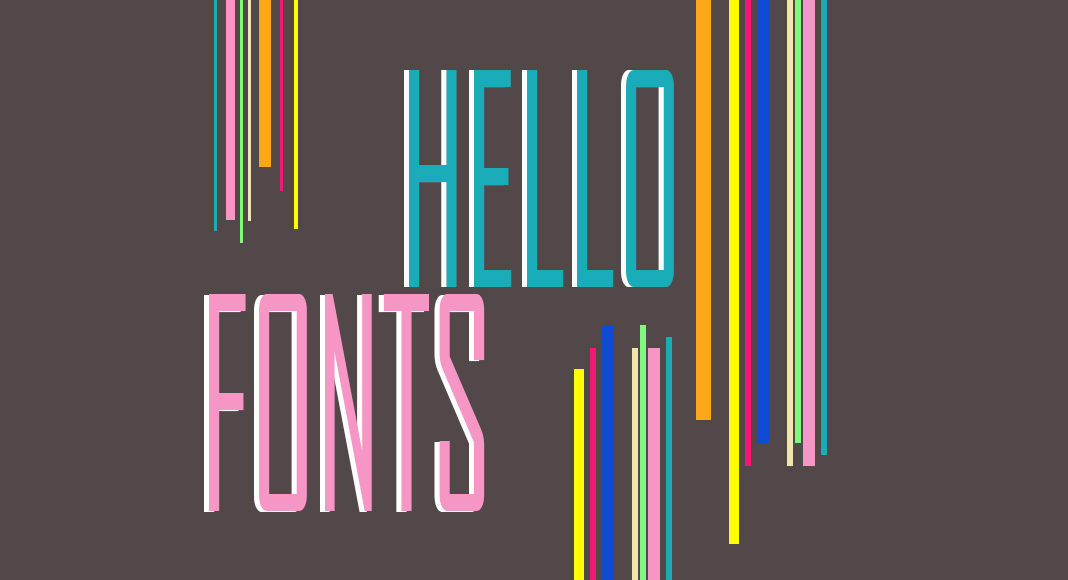
Manchmal geht es nur um wenige Millimeter. Statt beim herkömmlichen Font zu spationieren, bietet es sich an, von Anfang an eine schmale Schriftart zu wählen. Doch auch aus stilistischen Gründen kann sich ein engeres Schriftbild gutmachen. In unserer Sammlung unten findet sich für jeden Geschmack und Anlass etwas.
Schmale SchriftartSaira Condensed
Saira Condensed bietet insgesamt neun Schriftschnitte. Wünschen Sie die Schrift noch etwas komprimierter, finden Sie in den Google Fonts zudem Saira Extra Condensed.
Stint Ultra Condensed
Trotz seines extrem schmalen Schriftbilds ist Stint Ultra Condensed gut lesbar.
• Design: Astigmatic One Eye Typographic Institute
Schmale SchriftartCabin Condensed
Diese schmale Schriftart ist eine komprimierte Variante der Cabin-Schriftfamilie, für die sich die Designer von Schriften von Eric Gill und Edward Johnston inspirieren ließen.
• Design: Impallari Type
Schmale SchriftartBarlow Condensed
Barlow Condensed ist ein Kind Kaliforniens. Zumindest ist es der Schrift auf Straßenschildern und Autokennzeichen des Golden State nachempfunden.
Blue Highway
Highway meint in diesem Fall tatsächlich die Autobahn, und zwar die im Norden der USA und in Kanada. Von den Schildern auf diesen Schnellstraßen stammt die Vorlage für diesen Font.
Schmale SchriftartCopper Canyon
Der Font basiert auf Adobe Poplar, ist aber deutlich massiver.
Wire One
Schmal und dünn zugleich, dazu ein Hauch von Jugendstil: Wire One steht für elegantes Understatement.
Campanile
Mittelalter oder Jugendstil? Campanile weckt beide Assoziationen und bietet verspielte Details auf wenig Raum.
Schmale SchriftartNeumann
Die Designer orientierten sich an Didone-Schriften und bezeichnen ihren eigenen Font als robust und „mechanisch“.
Chursaechsische Fraktur
Gebrochene Schriften können sehr ausladend sein. Die Chursaechsische Fraktur fällt jedoch erfreulich schmal aus, sodass wenig Platz genügt.
Schmale SchriftartBewilder
Kalligrafie verbreitet immer etwas Nostalgie; so auch die Schrifart Bewilder, die aber auch als futuristisch durchgehen kann. Eignet sich explizit auch für kleine Schriftgrade.
Schmale SchriftartQuimbie
Mondän und nonchalant präsentiert sich der Art-déco-Font, den es auch in einer 3D- und einer Shadow-Variante gibt.
HermeneusOne
Der komprimierte Serifen-Font ist in jedem Schriftgrad gut zu lesen und eignet sich ganz besonders, wenn große Textmengen unterzubringen sind.
• Design: Rodrigo Fuenzalida